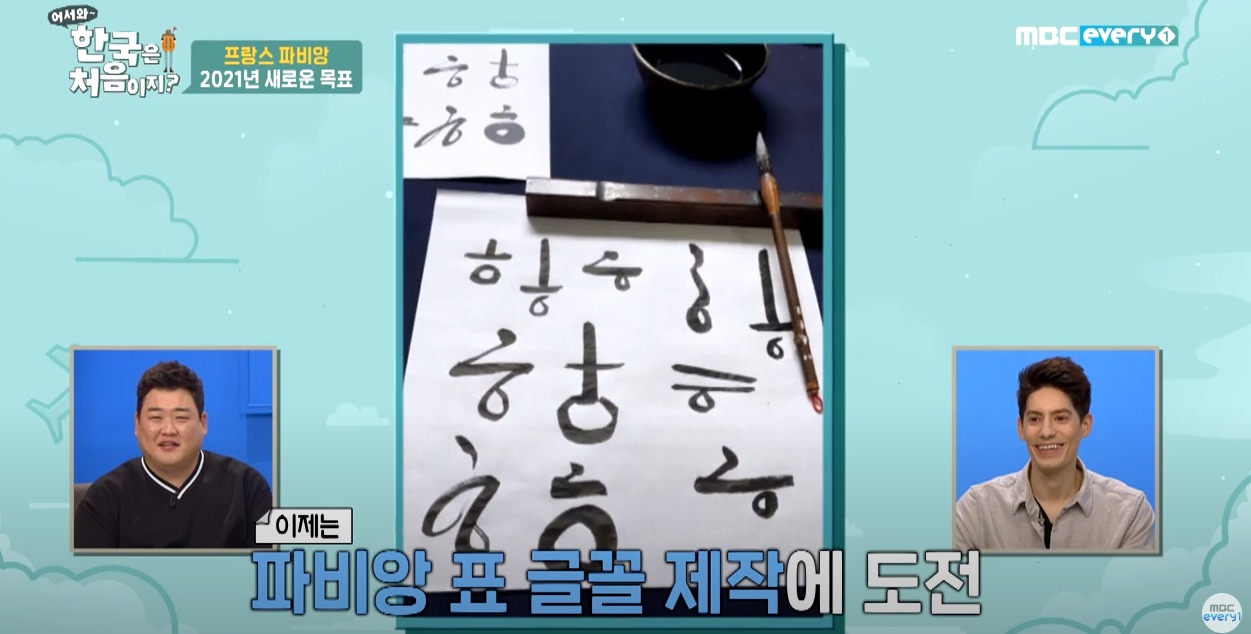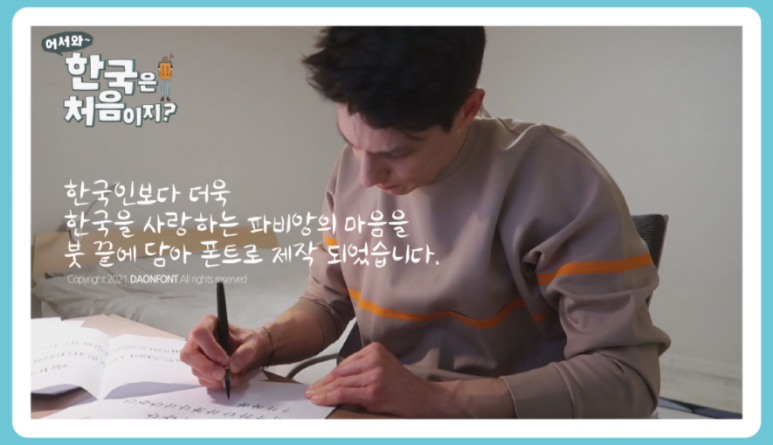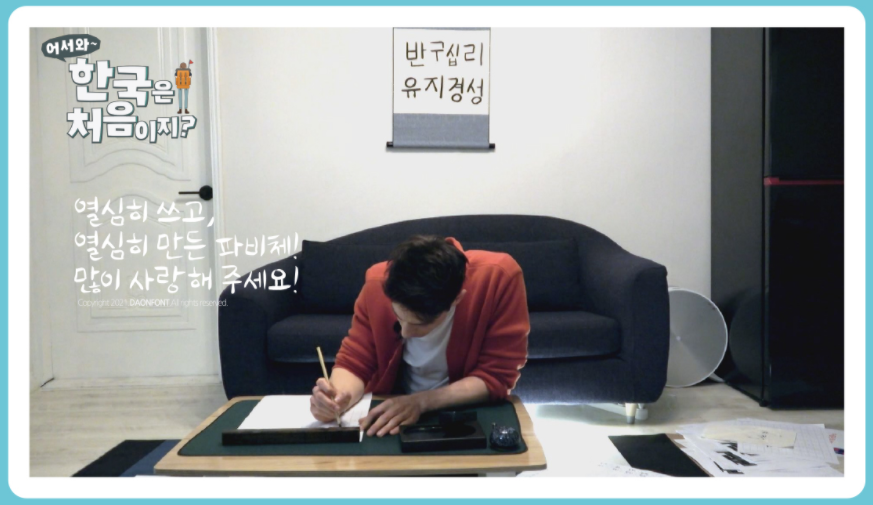
파비앙 폰트 다운로드 (무료) - 캘리그라피
한국에서 프랑스인으로 활동하고 있는 파비앙
한국에 대한 태권도와 한국에 대한 사랑, 지식을 바탕으로 유튜브와 공중파 프로그램에서 활발하게 활동하고 있어서
방송도 재미있게 보고 있는데요. 프로그램을 통해서 폰트를 만들고 무료 배포한적이 있었네요.
폰트가 제 생각보다 훨씬 이뻐서 다운로드 받고 디자인 할 때 종종 사용할까 합니다.